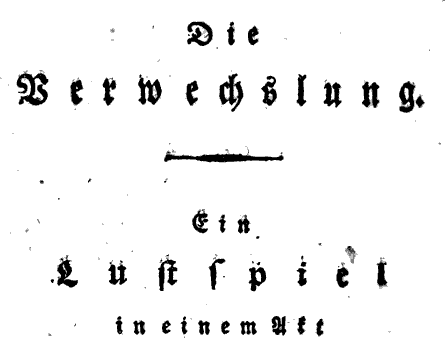
ſl-Ligatur in Verwechſlung?
Die Frage steht ja eigentlich schon im Titel, gehört in Verwechſlung bei Schreibung mit ſ und vorhandener Ligatur eine rein oder nicht? Ich bin jetzt nicht klar, wo die Morphemgrenze ist.
Ver·wechs·lung
Also keine Ligatur (und in der Fraktur kein ›ſ‹)
Doch natürlich ein ſ:
[…] Das gilt auch dann, wen ein sonst im Silbenanlaut stehnder s-Laut durch den Ausfall eines unbetonten e in den Auslaut gerät. Beispiele: auserleſne (für: auserleſene}, ich preiſ (für: ich preiſe) […]
So oder so ähnlich in 3 Duden-Auflagen, 1953, 1967, 2002 zu finden.
Doch natürlich ein ſ …
Ganz so eindeutig ist der Befund nicht: Der erste Duden von 1880 schreibt Verwechſelung mit ſ und Verwechslung mit s. Der Duden von 1926, von 1929 und »Das deutsche Wort« von Pekrun (1933) kennt Verwechſ(e)lung nur mit ſ.
Von einer Ligatur würde ich jedenfalls abraten.
Wie Stefan schon angedeutet hat, ist in Verwechslung ein e ausgefallen; das Wort setzt sich zusammen aus Ver + wechsel + ung. Es ist also auf jeden Fall mit langem s zu schreiben (1880 waren die Regeln noch nicht so gefestigt).
Möchte man verdeutlichen, daß ein e ausgefallen ist, setzt man es ohne Verbund, dann aber am besten mit Auslassungszeichen: Verwechſ’lung.
Ansonsten mit Verbund. Der Fall entspricht im Grunde Wörtern wie kreiſt, loſt usw., in denen auch ein e ausgefallen ist, und die dennoch mit Verbund gesetzt werden.
Schnitzel: Die Silbentrennung hat nichts mit der S-Schreibung zu tun.*
* Außer geschichtlich.
Ganz so eindeutig ist der Befund nicht: Der erste Duden von 1880 schreibt Verwechſelung mit ſ und Verwechslung mit s. Der Duden von 1926, von 1929 und »Das deutsche Wort« von Pekrun (1933) kennt Verwechſ(e)lung nur mit ſ.
Mackenſen Deutſche Rechtſchreibung (1. Auflage, April 1954) entſpricht dem Duden von 1880 und ſchreibt ebenfalls Verwechſelung mit ſ und Verwechslung mit s. Daran hätte ich mich orientiert, aber nach Leſen dieſes Fadens bin ich faſt ſicher, daſs Verwechſlung richtig(er) iſt.
Überprüft man das mal bei Google Books ist der Befund eindeutig:
Verwech_s_lung vs. Verwech_ſ_elung. Ich habe keinen einzigen Beleg für Verwech_ſ_lung finden können.
Überprüft man das mal bei Google Books ist der Befund eindeutig:
Verwech_s_lung vs. Verwech_ſ_elung. Ich habe keinen einzigen Beleg für Verwech_ſ_lung finden können.
In einigen Wörterbüchern, auf totem Baum gedruckt, findet man die Schreibweiſe „Verwechſlung“. Google ist nicht der Maſsſtab für Rechtſchreibung ... und Wikipedia nicht für Wiſſenſchaft. Die beiden haben mit den jeweiligen Themen etwa ſo viel zu tun wie ich mit gutem Geſchmack.
Na ja, Google setzt ja keine Rechtschreibregel sondern dokumentiert hier ja nur das Vorhandene, und da ist es schon bemerkenswert, daß der Google-Befund mit der ursprünglichen Vorgabe Konrad Dudens zusammenfällt.
… Google ist nicht der Maſsſtab für Rechtſchreibung ... und Wikipedia nicht für Wiſſenſchaft. Die beiden haben mit den jeweiligen Themen etwa ſo viel zu tun wie ich mit gutem Geſchmack.
Du musst schon genau hinschauen: Es war von "Google Books" die Rede, nicht von der Suchmaschine "Google". "Google Books" macht nichts anderes, als dne Inhalt von Büchern wiederzugeben. Ob du nun in die Bibliothek läufst und selbst umblätterst oder das dem Browser überlässt, ändert nichts am Ergebnis.
In einigen Wörterbüchern, auf totem Baum gedruckt, findet man die Schreibweiſe „Verwechſlung“. Google ist nicht der Maſsſtab für Rechtſchreibung ... und Wikipedia nicht für Wiſſenſchaft. Die beiden haben mit den jeweiligen Themen etwa ſo viel zu tun wie ich mit gutem Geſchmack.
Es geht ja auch nicht darum, Google, Google Books (oder eine andere Suchmaschine) als einzig gültigen Maßstab zu propagieren, sondern darum, die Suchmaschinen zu nutzen, um auf sehr unkompliziertem Wege und auf die Schnelle eine erste Tendenz zu einem Sachverhalt zu ermitteln. Das ist in meinen Augen eine akzeptable Methode, sofern man sich nicht einzig auf diese Quelle verlässt, sondern sie im Anschluss durch eine umfassende Recherche weiterer wissenschaftlicher Quellen ergänzt. :-)
Das Problem ist, daß praktisch alles mögliche vorkam. Die Satzregeln waren selten klar definiert, Faustregeln waren in Setzereien üblich. Die wohl am weitesten verbreitete Faustregel war, daß am Silbenende das runde s verwendet wird. Das stimmte auch in den meisten Fällen. In deutschen Wörtern kommt eine Silbengrenze, die keine Wortgrenze ist, normalerweise nur in den Verbindungen st und sp vor: Wespe, Weste, knospen, hasten. Folgt auf das s irgendein anderer Buchstabe, handelt es sich in der Regel um eine Wortfuge. Man setzte also gemäß der Faustregel am Silbenende das runde s, außer es folgte ein p oder t, denn da sagte das Sprachgefühl deutlich, daß die beiden Silben zu einem Wortteil gehören.
Ein ausgefallenes e war nun aber problematisch. In Verwechslung ist nicht auf Anhieb ersichtlich, daß das l zum Wortstamm gehört, man neigt dazu, es wegen der Silbenaufteilung zur Endung zu zählen (siehe Frakturfreaks Erklärung, daß er sich über die Morphemgrenzen unklar sei!), zudem spricht die Folge sl eben für eine Wortfuge, da sie innerhalb deutscher Wörter an einer Silbengrenze normalerweise nicht vorkommt. Also setzte man das runde s — Setzer waren halt keine Sprachwissenschaftler.